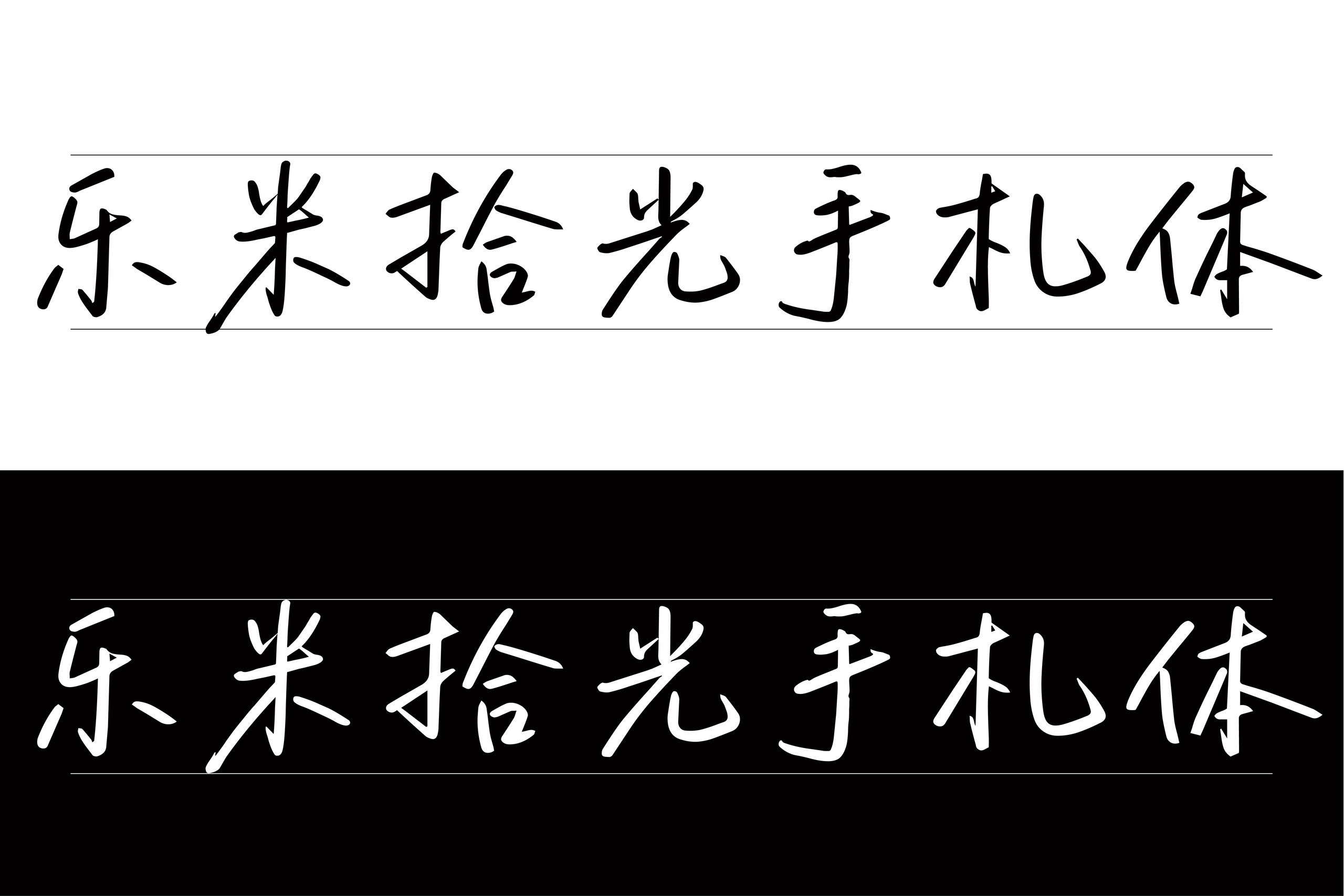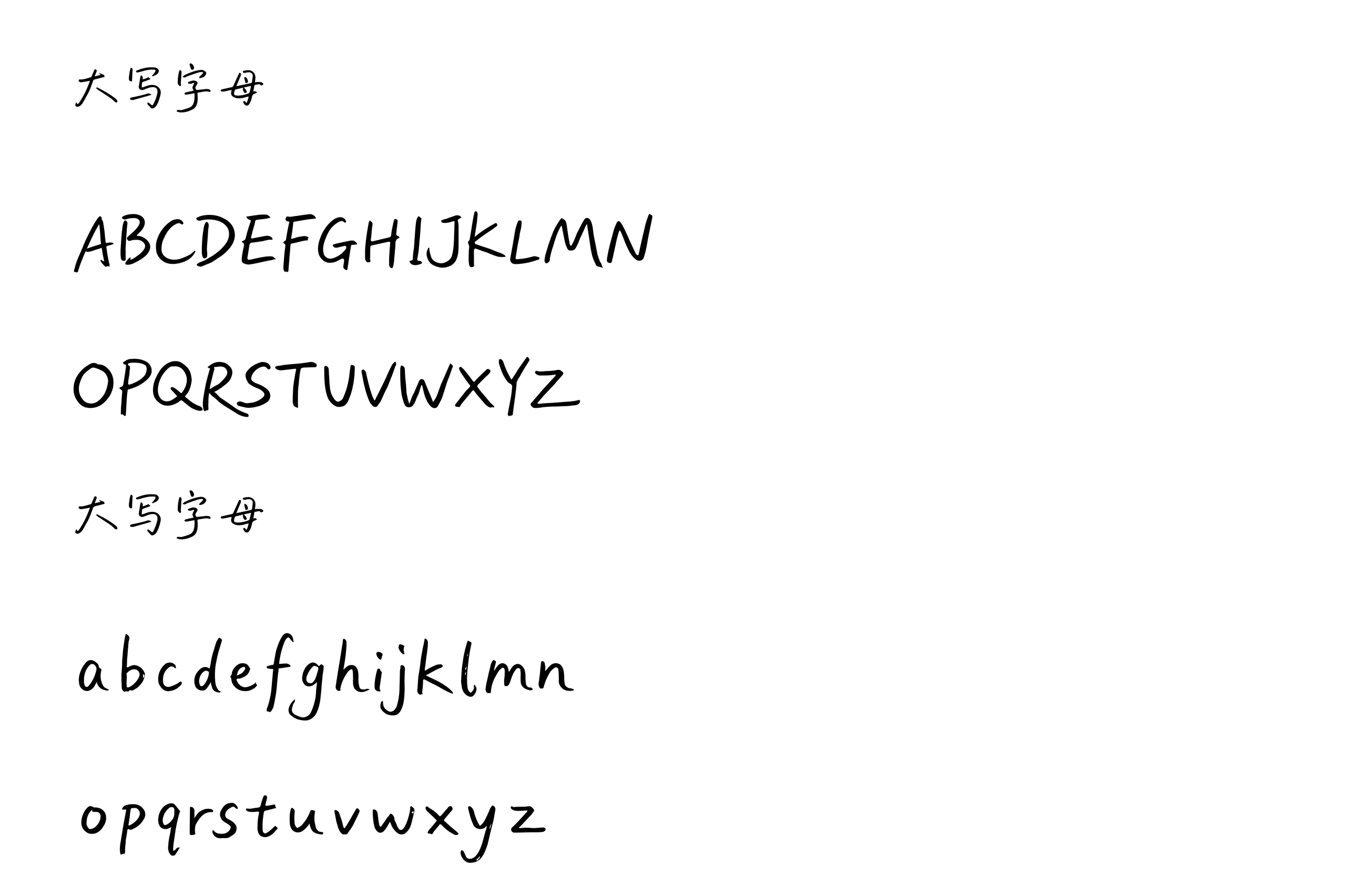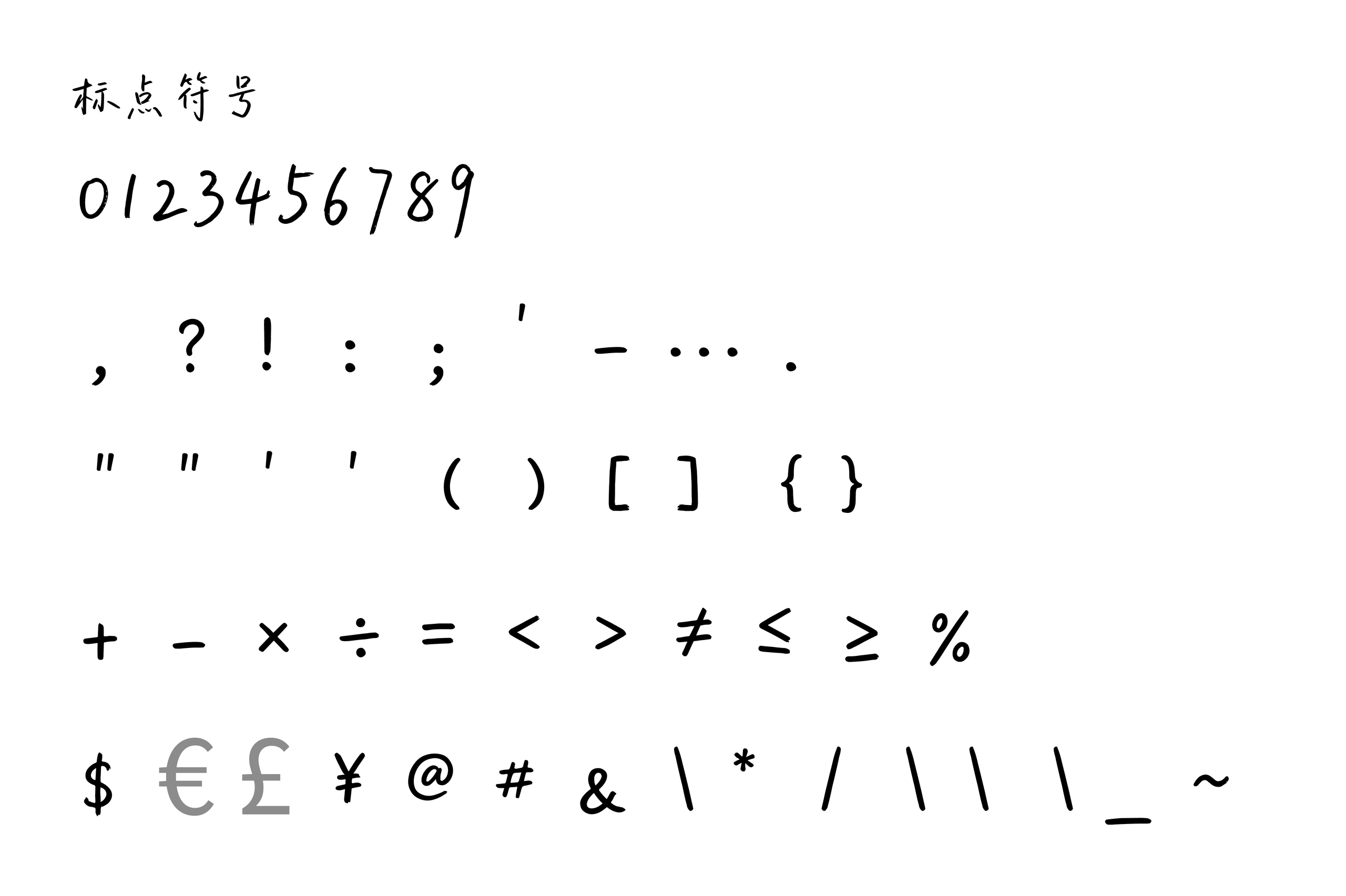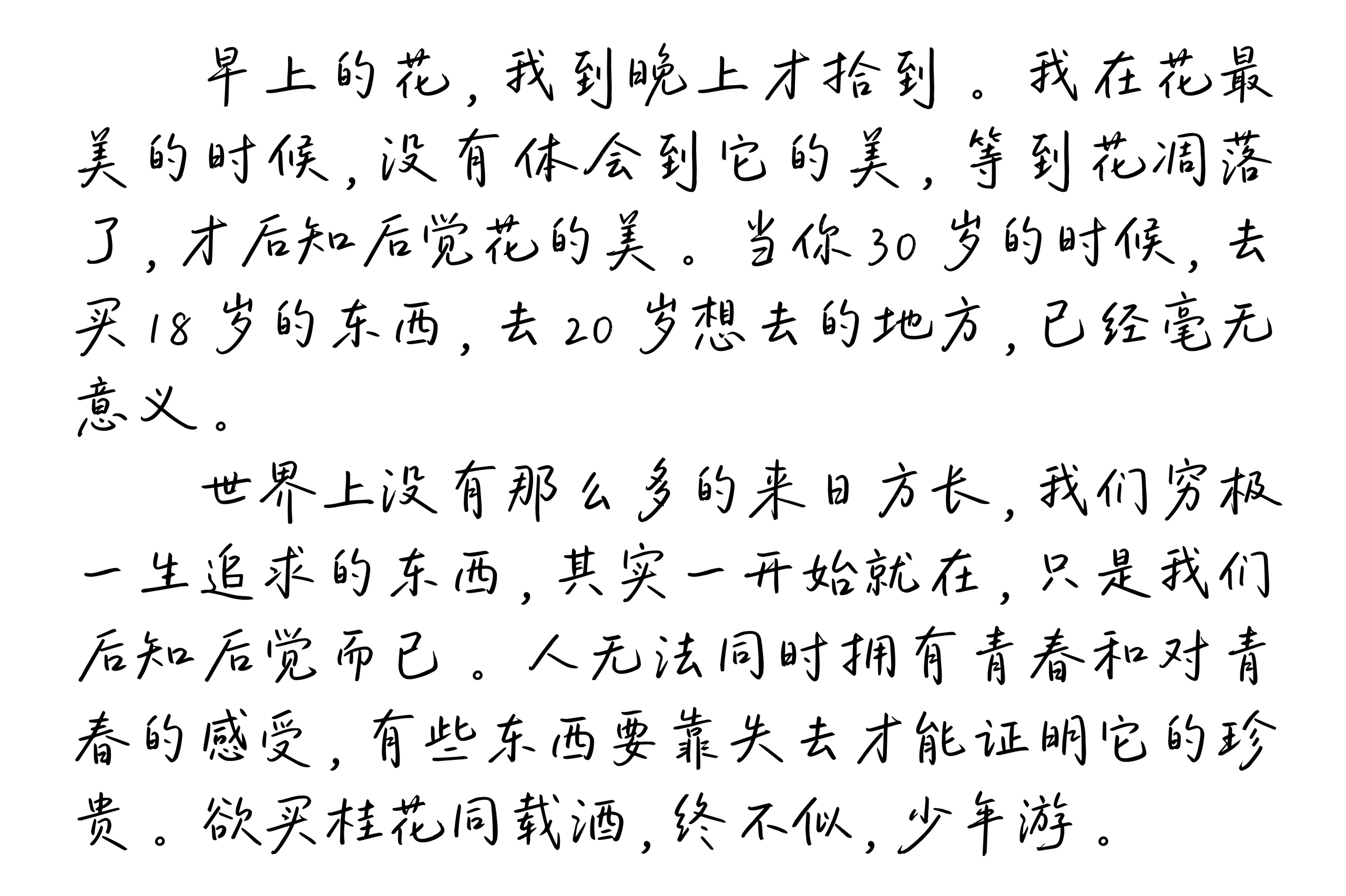
乐米拾光手札体
乐米拾光手札体是一款由杭州乐米网络科技有限公司发布的中文手写字体,并提供免费商用授权。字体以自然书写为基础,将轻盈随性的手写笔触融入字形设计之中,整体笔画纤细舒展,结构自然灵动,保留了真实书写中自然流露的节奏感,让文字呈现出清新、温柔而富有生活气息的视觉风格。
乐米拾光手札体:笔画纤细自然轻盈舒展的字体
从字形表现来看,乐米拾光手札体没有刻意追求传统印刷字体的规整感,而是通过自然的笔画走势和轻微的结构变化,还原日常书写中的随性感。横竖撇捺之间收放自然,笔画起收轻巧,字形整体呈现出较为松弛的状态。这样的设计让字体拥有明显的手写质感,同时又保持了良好的辨识度,既不会过于潦草,也不会显得刻意装饰。
乐米拾光手札体:笔画纤细自然轻盈舒展的字体
字体的英文部分同样延续了中文的手写风格,大写字母简洁利落,小写字母自然流畅,搭配数字及常用标点后,整体视觉保持统一。中文、英文与数字混排时,不同字符之间能够形成协调的笔触关系,使整套字体在实际设计中具有较好的完整性。
乐米拾光手札体:笔画纤细自然轻盈舒展的字体
乐米拾光手札体整体气质轻松而自然,没有强烈的商业设计感,更像是随手写在纸上的一段文字。它适合表达生活记录、个人感受以及轻松温暖的情绪,在字体与内容结合之后,能够让文字拥有更加明显的亲和力和故事感。无论是简短的生活文案,还是具有情绪表达的长句,都能够通过这种自然的手写质感,为画面增加细腻的人文气息。
乐米拾光手札体:笔画纤细自然轻盈舒展的字体
在使用场景方面,乐米拾光手札体适合应用于手账、日记、生活方式海报、文艺短句、社交媒体配图、明信片、书籍内页、文创设计、宣传物料以及互联网内容等场景。尤其适合搭配摄影、插画和留白版式使用,让纤细的手写笔画成为画面中的情绪表达,为整体设计带来更加轻松、自然的视觉体验。
乐米拾光手札体以自然轻盈的笔触记录生活,用不刻意规整的字形保留手写文字独有的温度。对于喜欢清新、文艺、自然手写风格的设计师和创作者来说,是一款适合用于表达日常情绪与生活质感的中文手写字体。